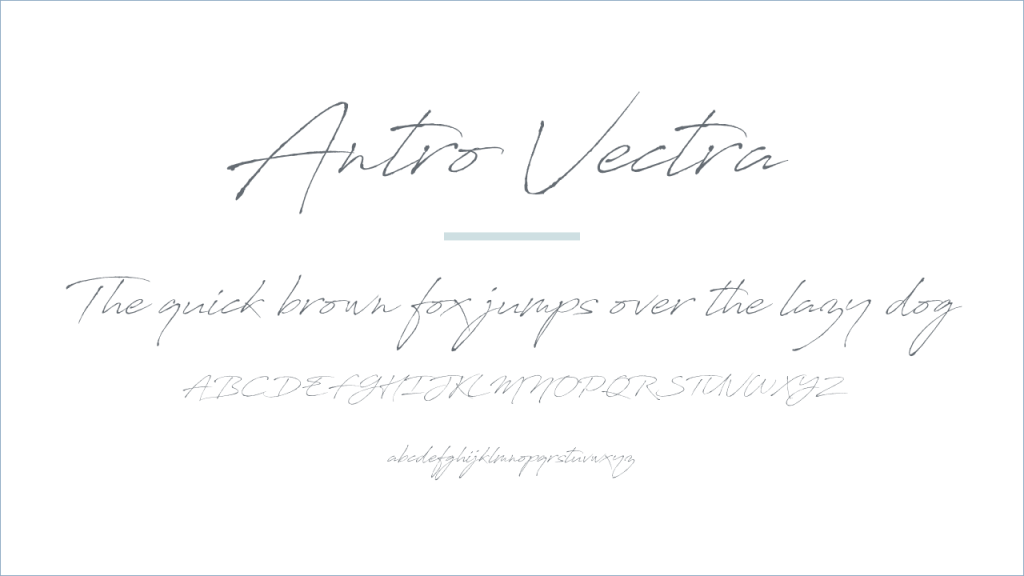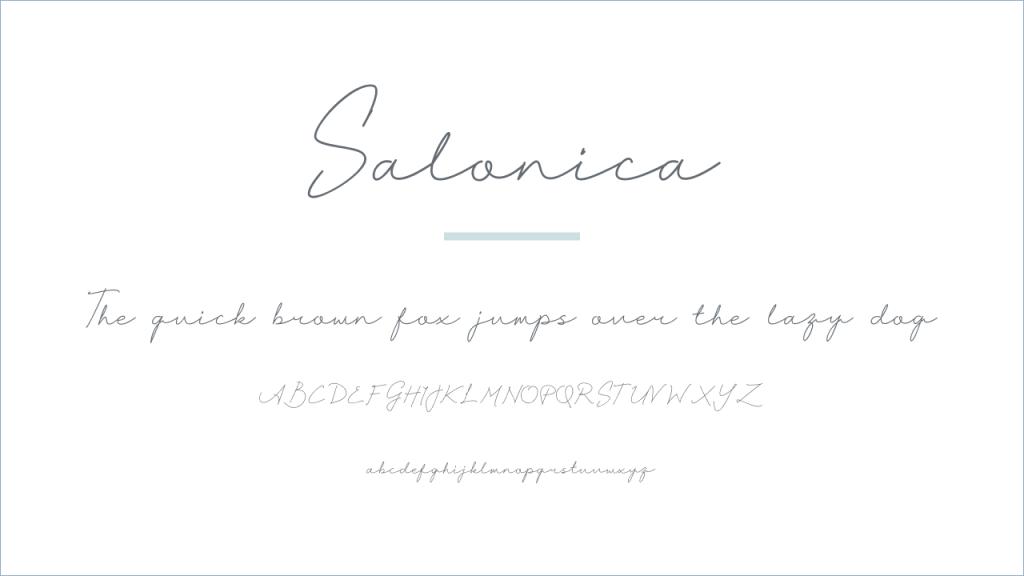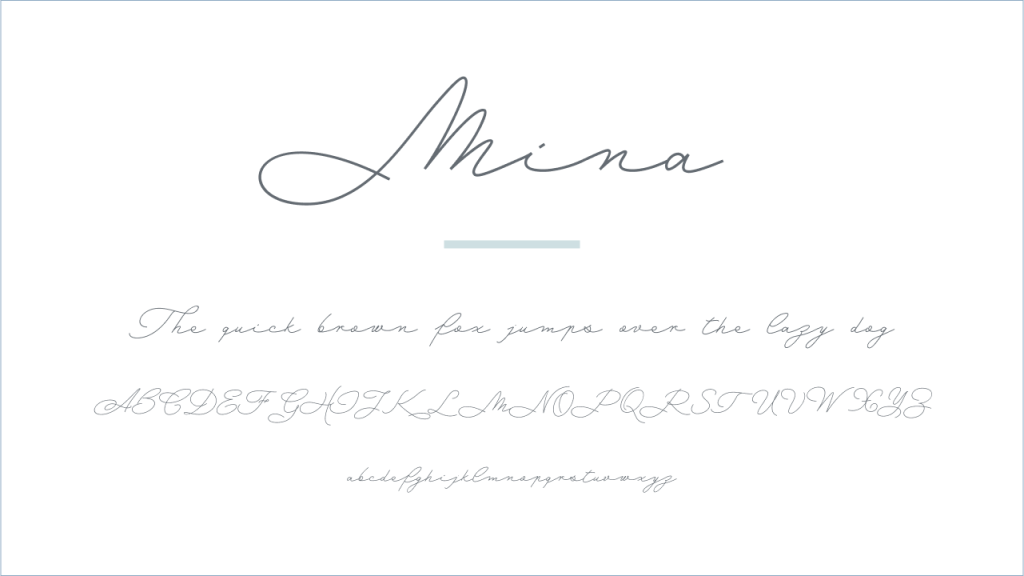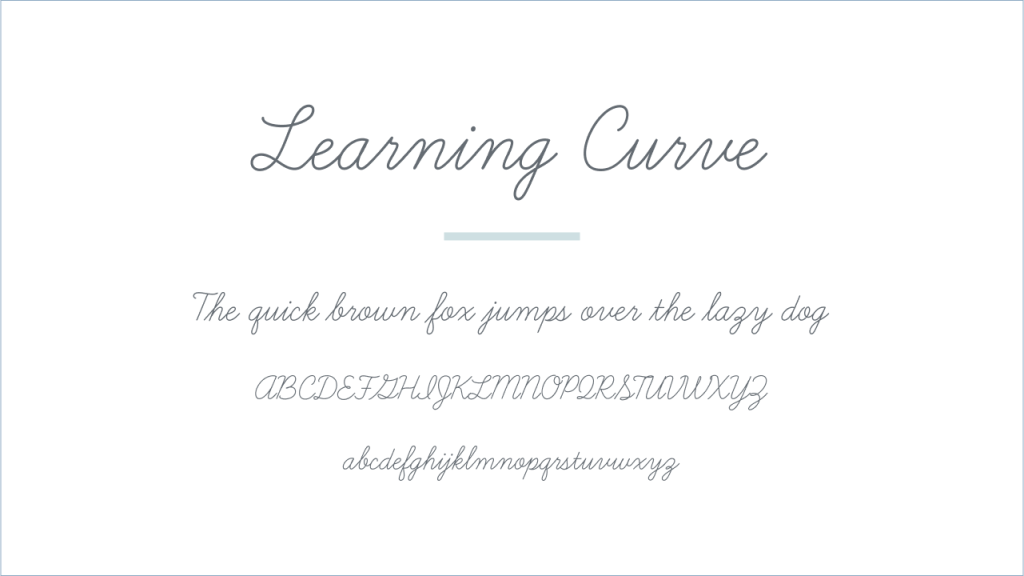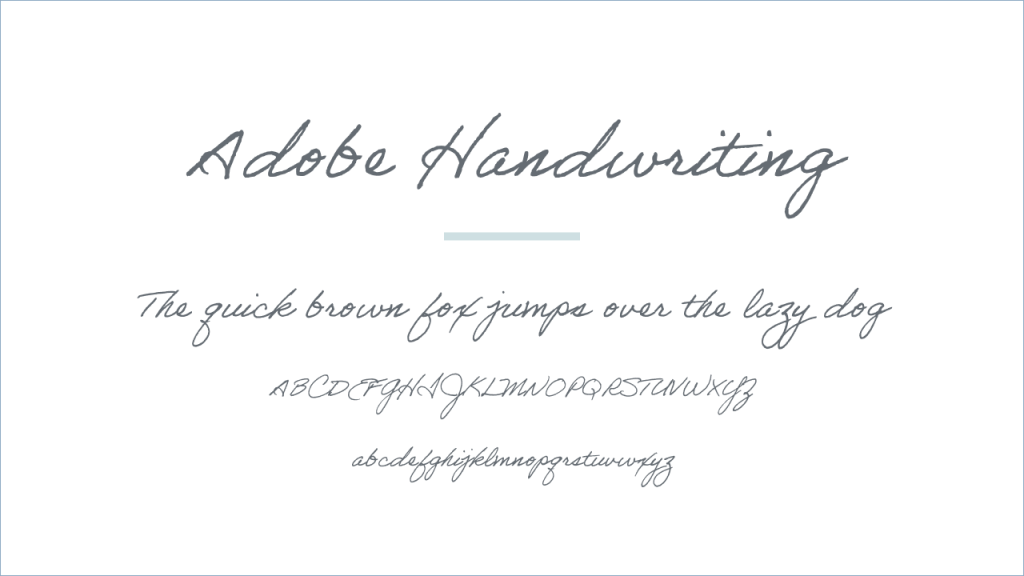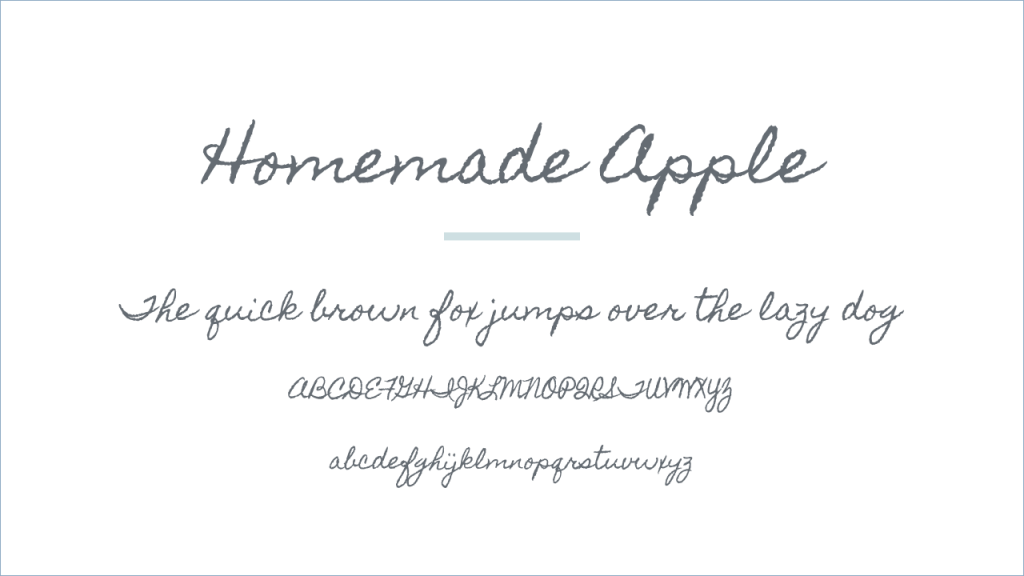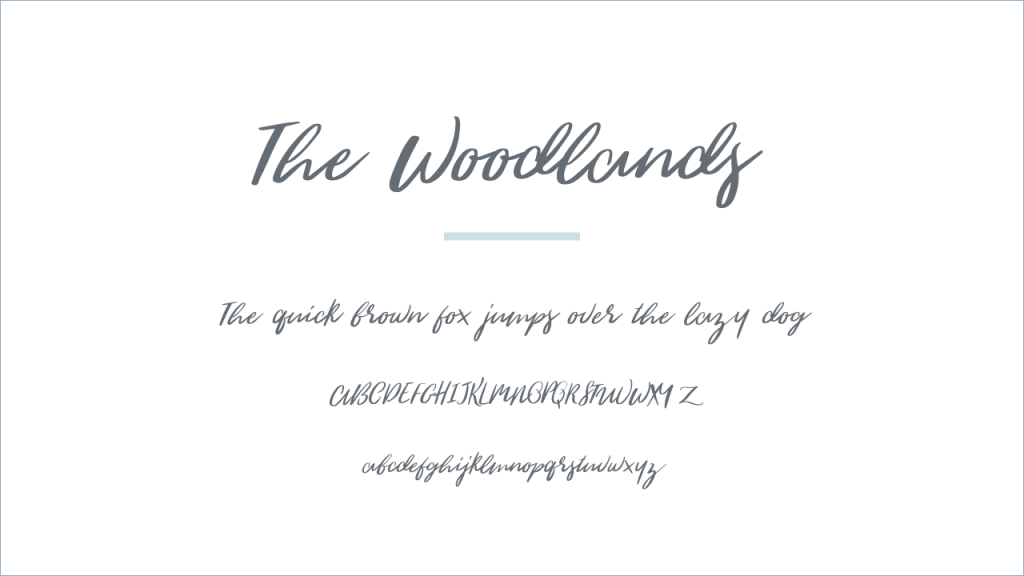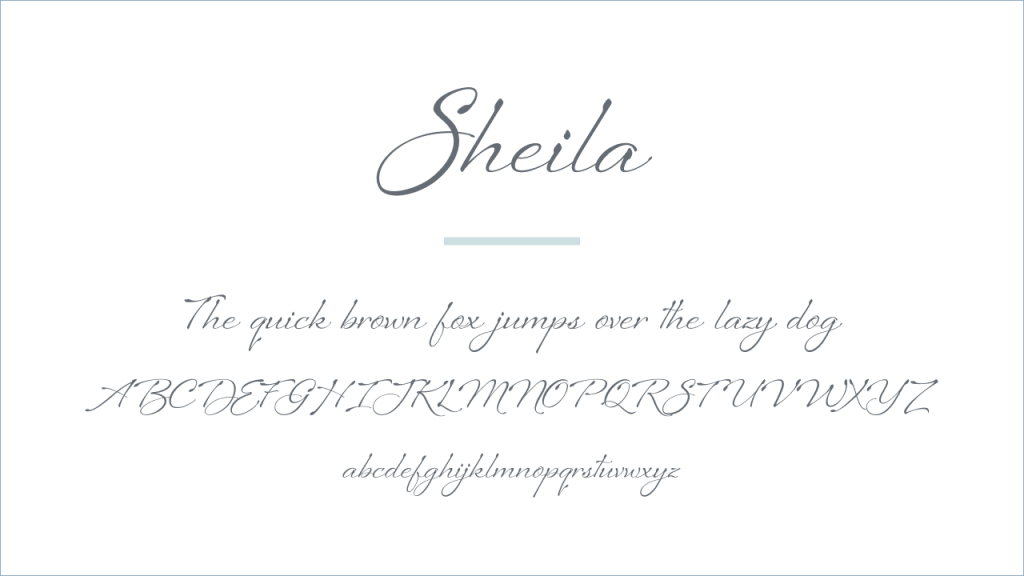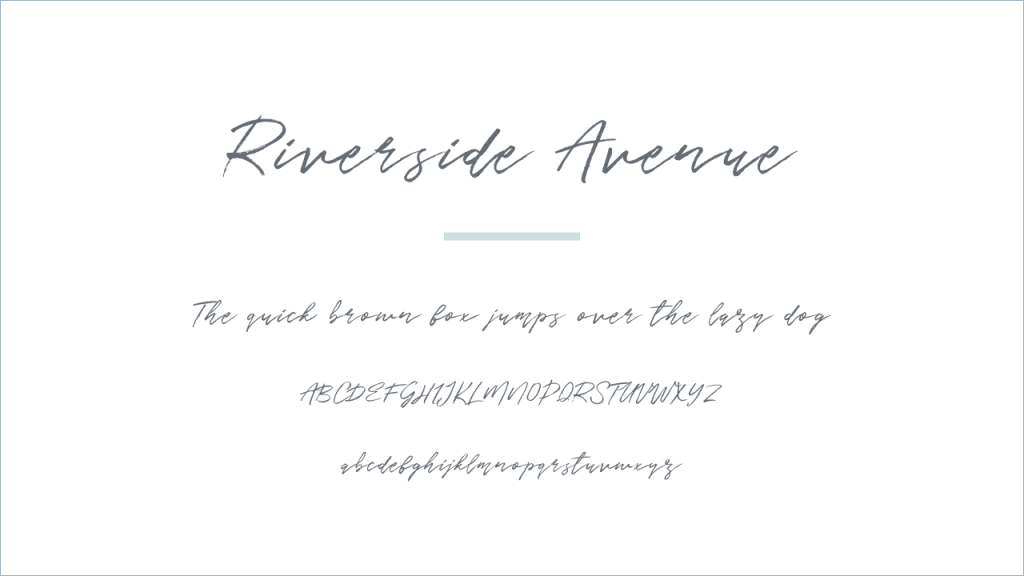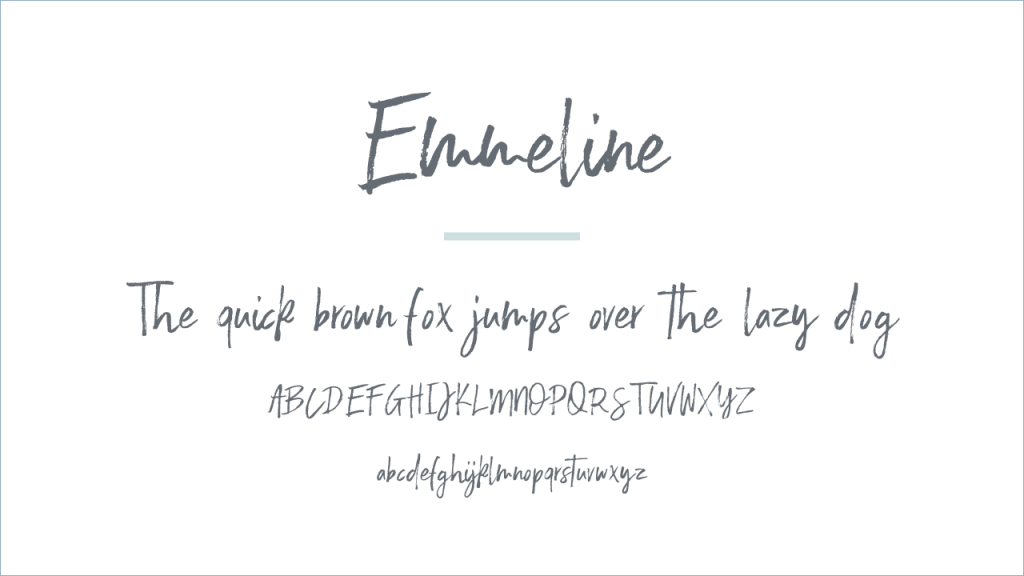
このページでは、欧文書体(アルファベット、数字、記号など、欧米で使われる文字の総称)の魅力的な手書き風フリーフォントをご紹介します。
手書き風フォントは、柔らかな印象からクラシカルな雰囲気まで、さまざまなスタイルで個性が光ります。デザインに合わせて最適なフォントを見つけてください。
Sheila
Antro Vectra
Salonica
フォントスタイル | Regular |
収録文字 | 英数字、記号 |
デザイナー | Novan Esthi Bimo Santosa |
Mina
フォントスタイル | Regular |
収録文字 | 英数字、記号 |
デザイナー | Giuseppe Salerno / Paco González |
Learning Curve
フォントスタイル | Regular / Bold |
収録文字 | 英数字、記号 |
デザイナー | Jess Latham |
Adobe Handwriting
フォントスタイル | 3種類 |
収録文字 | 英数字、記号 |
デザイナー | Ernest March / Frank Grießhammer / Tiffany Wardle de Sousa |
Homemade Apple
フォントスタイル | Regular |
収録文字 | 英数字、記号 |
デザイナー | Stuart Sandler |
The Woodlands
Riverside Avenue
Emmeline
フォントスタイル | Regular |
収録文字 | 英数字、記号 |
デザイナー | Sinikka Li |
Mi Teiyng Script
フォントスタイル | Regular |
収録文字 | 英数字、記号 |
デザイナー | WISIT PO |
Beautiful Heart
So Lovely
フォントスタイル | Regular |
収録文字 | 英数字、記号 |
デザイナー | Neil Summerour |
La Belle Aurore
amatic sc
フォントスタイル | Regular / Bold |
収録文字 | 英数字、記号 |
デザイナー | Ben Nathan / Eugene Spizhovy / Vernon Adams |
Foxhole
KG Two is Better Than One